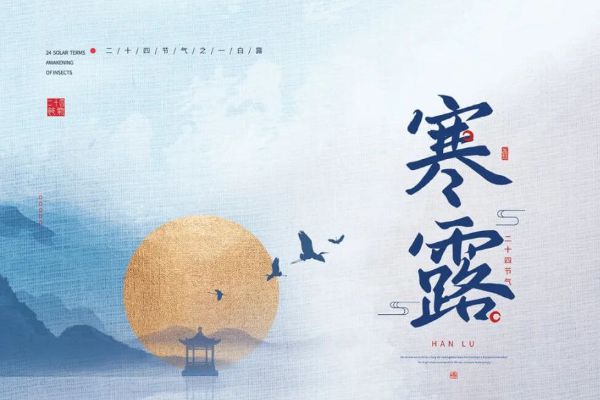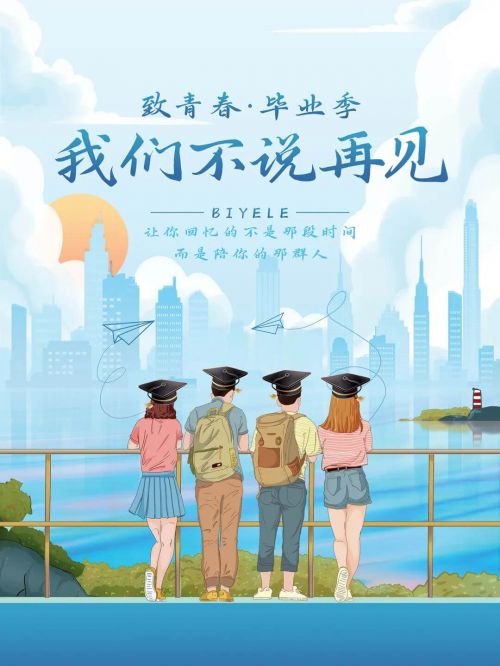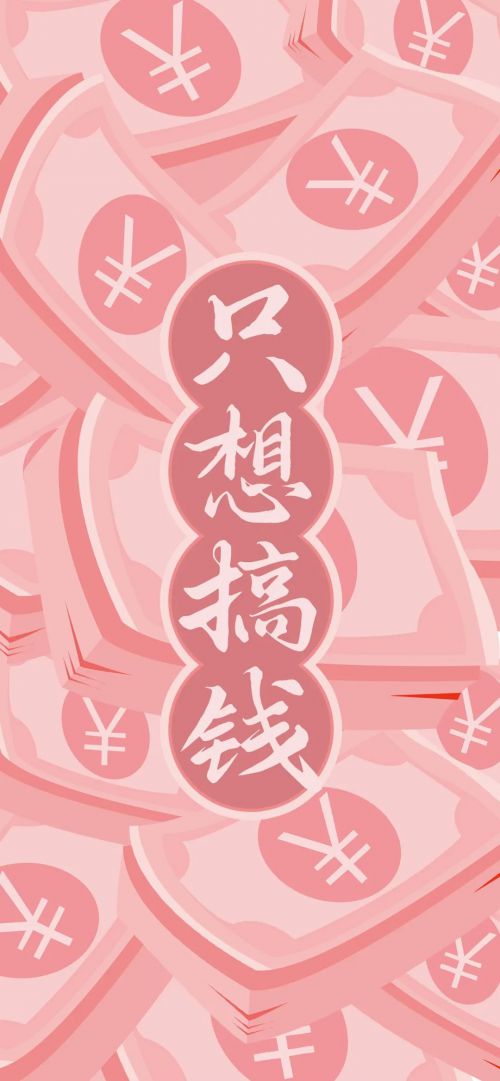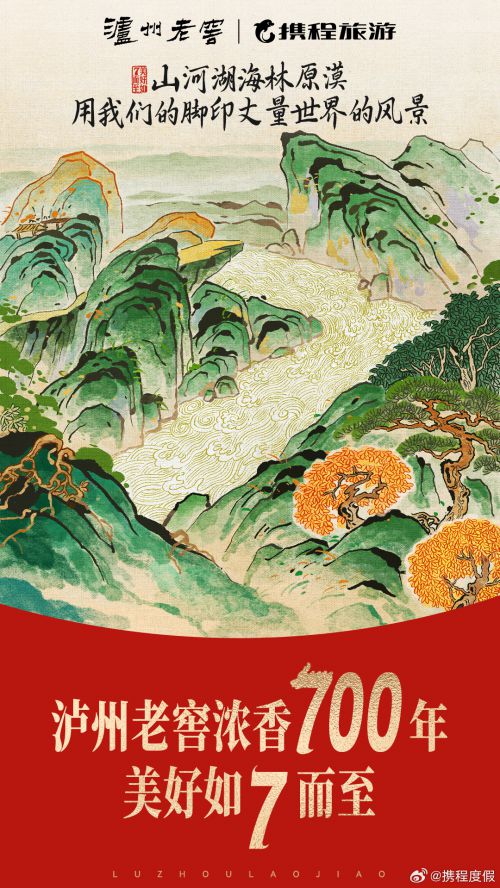
鸿雷行书简体
鸿雷行书简体是由鸿雷字记推出的手写体字体,以行书为创作基底,融合手写风的灵动与自然,是兼具艺术表现力与实用价值的免费商用字体。 从字形结构来看,鸿雷行书简体整体修长,重心居中,中宫适中,布局舒展而不失平衡——修长的字形赋予文字飘逸感,居中的重心与适中的中宫则保障了阅读时的稳定性,让行书的洒脱与实用的易读性巧妙融合。 笔型设计是鸿雷行书简体的核心亮点:以行书流畅特质为骨架,笔画走势自然灵动,大量连笔设计让文字如手写般一气呵成,笔画间的连贯感尽显书写时的韵律;起笔与收笔处更暗藏巧思,尖锋的利落与圆润的柔和相互映衬,既保留了行书的经典韵味,又注入手写的温度与细节。 笔画粗细上,鸿雷行书简体保持适中且均匀的笔触,避免了过粗或过细导致的视觉失衡,无论是标题放大还是内文缩小,都能呈现清晰、舒适的视觉效果。 作为免费商用字体,鸿雷行书简体适用于海报设计、品牌标语、手账排版、文艺文案等多元场景,手写风的独特质感能为内容增添自然气息,是设计师与创作者打造个性视觉的实用之选。